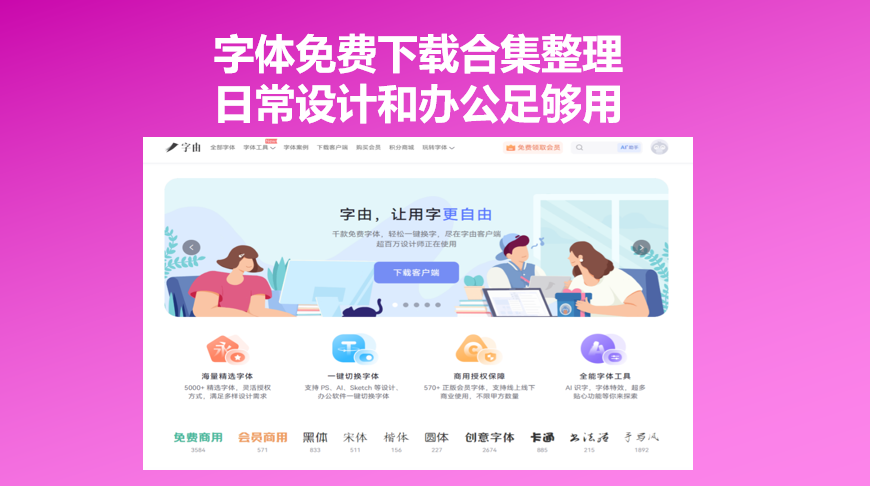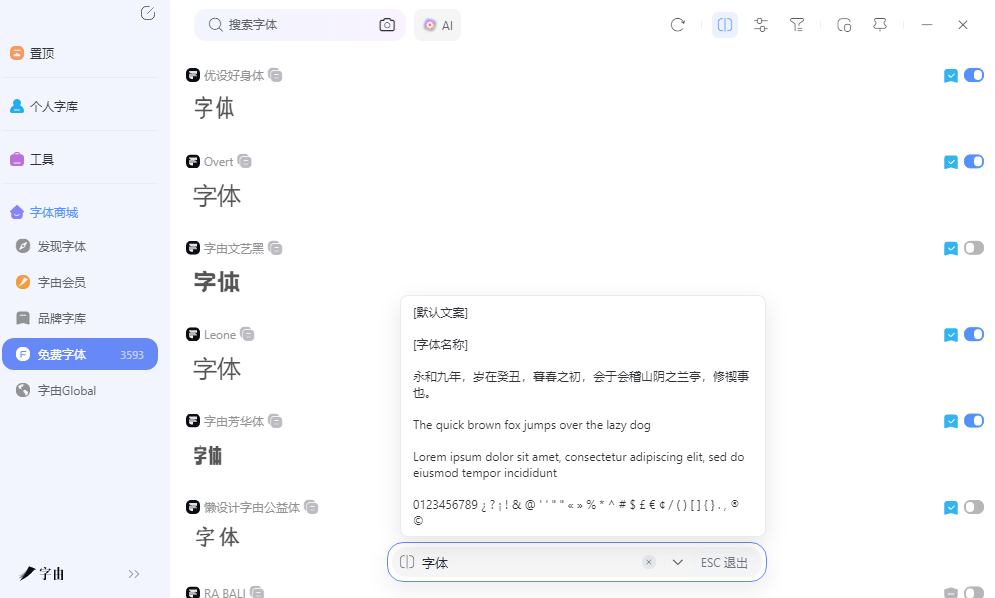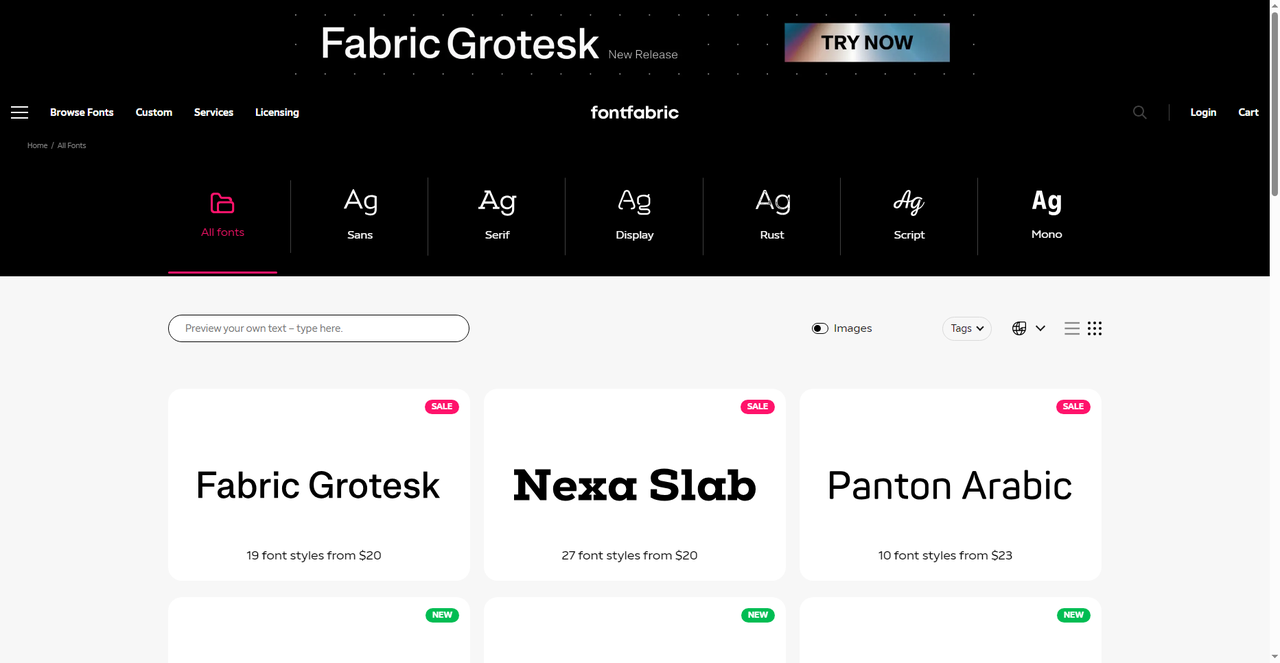
字体免费下载合集整理,日常设计和办公足够用
整理电脑里的字体文件夹,发现里面塞满了从各个论坛、网盘下载的文件,有些连名字都是乱码,有些安装后显示异常,还有些根本不知道能不能商用。其实与其零散地到处搜,不如直接收藏几个靠谱的字体免费下载平台,按需取用反而更高效。这篇文章整理了五个实用网站,从中文到英文、从通用到特殊场景都有覆盖,每个平台都标注了授权信息和适用场景,日常设计和办公基本够用了。
字由中明确标注可免费商用的中文字体超过三千款,但是很多人平时搜集字体,文件夹命名乱七八糟,真到做项目时却想不起来哪款能商用,但是字由把授权信息直接标在每款字体的详情页,免费商用标签一眼就能看见,勾选后列表里只剩能放心用的选项,做公司 PPT 或者商业海报时从这里挑,后续不用担心。
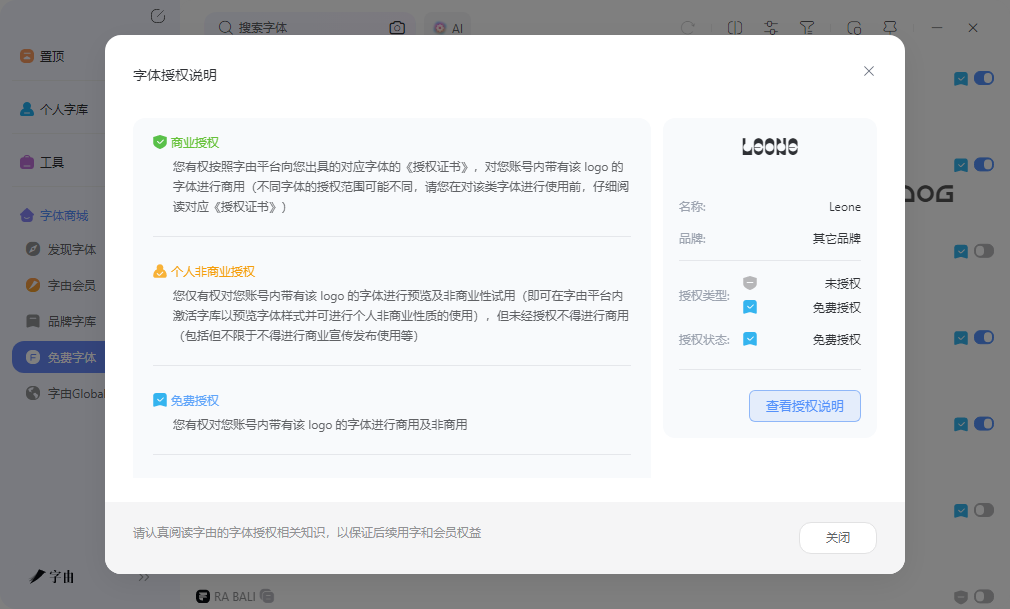
浏览方式也做了不少优化。除了常见的黑体、宋体、楷体、行书这些基础分类,还按使用场景和视觉气质做了细分。比如要做年会海报,直接点进喜庆或者中国风标签;要做科技类 PPT,筛选现代或者商务分类。这种按场景找字的方式比按书体名称翻找更直观,尤其是对字体知识不多的办公用户来说,看到标签就能大概猜出风格方向,找字体免费下载资源时效率提高不少。
预览环节也省了不少事。传统方式是先下载安装,再到软件里试效果,不合适再卸载,来回折腾。字由支持在预览框里直接输入自己的文案,字号、背景色都能调,看到实际排版效果再决定要不要激活。这个细节对判断字体在真实项目中的表现很管用,同样的字体显示不同内容,视觉感受可能差很多。遇到合适的点一下收藏,自动归到个人分组里,下次做同类项目直接打开分组调用,不用重新翻找。
而且字由对跨设备同步对多机工作的人比较友好。公司电脑上整理好的收藏和分组,回家登录同一个账号全部都在。换电脑或者系统重装后,登录账号就能恢复之前的字体设置,省去了重新下载安装几百款字体的麻烦。对于需要长期维护一套稳定字体免费下载资源的设计师和办公用户来说,这种云端备份比本地文件夹管理靠谱得多。
2、FontFabric
FontFabric 是一个专业字体厂商网站,首页展示了 Fabric Grotesk、Nexa Slab、Panton Arabic 等多款字体家族。每款字体都提供了详细的字重展示和风格预览,用户可以在搜索框里输入自己的文案测试效果。FontFabric 的字体质量比较高,很多字体家族包含多个字重和变体,适合做品牌 VI 或者完整排版系统。部分字体提供字体免费下载选项,下载前可以确认授权范围。对于需要高质量英文字体资源的设计师来说,这个平台的专业度比较可观。字体文件一般是 OTF 或 TTF 格式,安装到系统后就能在各类设计软件里调用。平台的界面设计简洁现代,浏览体验比较流畅,字体展示图清晰,能快速判断风格是否符合项目需求。
3、ReceiptFont
ReceiptFont 是一个专注收据和小票字体的特色平台,收录了超市收银机、热敏打印机常见的字体样式。首页展示了 Walmart、CVS、Target 等商场小票上常见的字体效果,包括点阵字体、等宽字体等类型。这些字体在日常生活中很常见,但普通字体库很少收录。对于需要模拟真实收据效果、做复古设计或者研究收银系统字体的用户来说,ReceiptFont 提供了很精准的字体免费下载参考。每款字体都标注了使用场景和来源说明,下载前可以了解清楚。字体文件格式通用,安装后在 Photoshop、Illustrator 里可以直接调用,做复古海报或者模拟小票的设计时很有特色。这个平台的资源虽然小众,但在特定场景下很难被替代,属于设计师工具箱里的特殊储备。
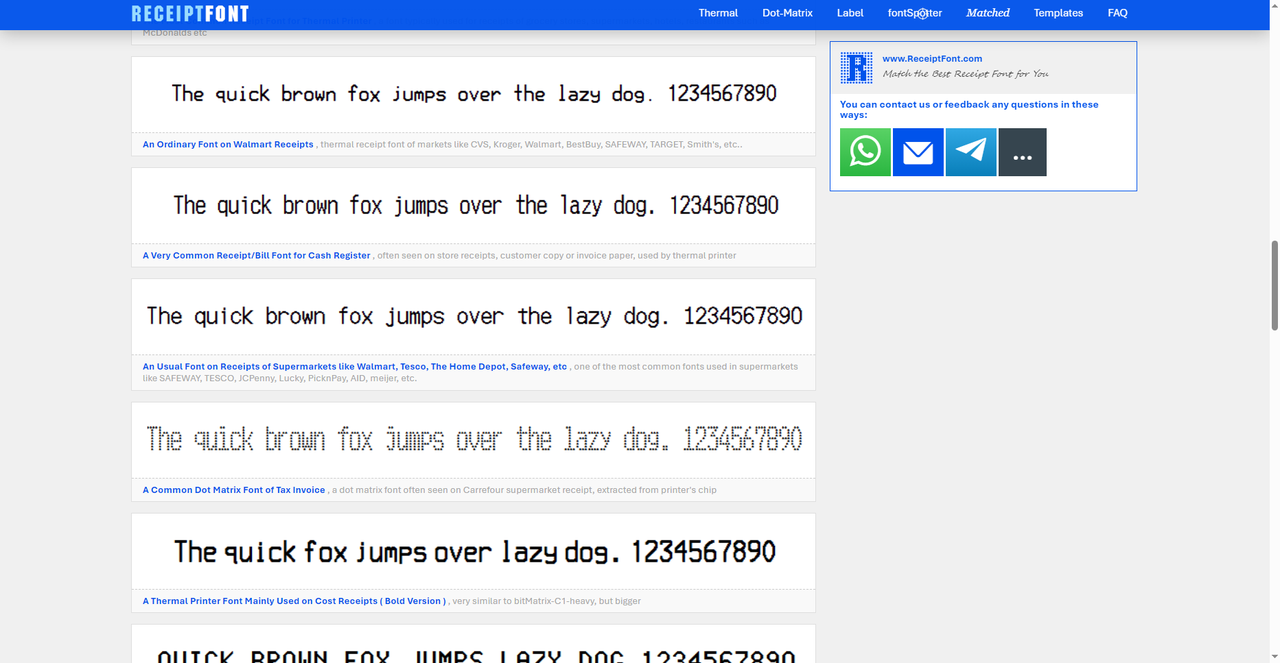
4、Cufon Fonts
Cufon Fonts 是一个字体集合平台,按主题整理了多个字体合集,包括 Happy Birthday Fonts、Editorial Fonts、Chinese Style Fonts、Tattoo Fonts、Study Fonts、Cinematic Fonts、Science Fonts 等。每个合集收录了风格相近的字体资源,方便用户按场景快速定位。比如做中国风海报可以直接浏览 Chinese Style Fonts 合集,做生日贺卡可以查看 Happy Birthday Fonts。平台的浏览方式比较直观,通过封面图就能判断合集的整体风格。部分字体支持字体免费下载,下载前需要确认具体授权信息。对于喜欢按主题探索字体、随机发现新资源的用户来说,这种合集整理方式比较省心。合集的更新频率比较稳定,经常会有新的主题加入,定期浏览可以发现一些意想不到的资源。
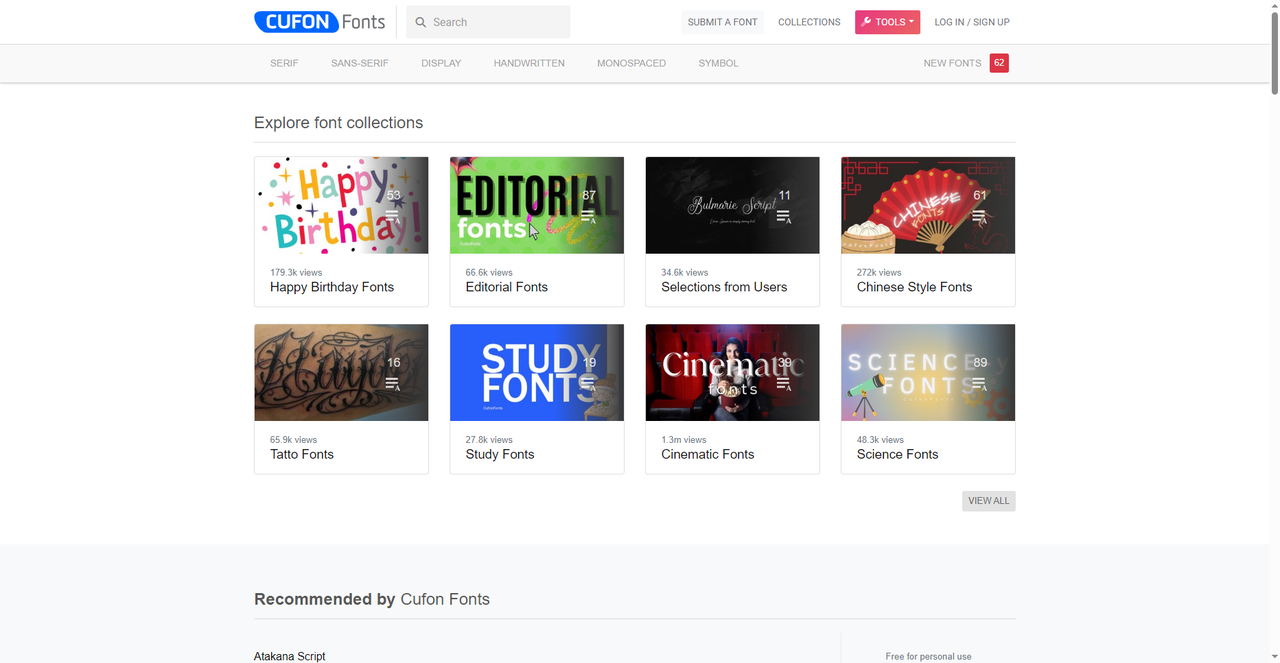
5、Font Squirrel
Font Squirrel 以 Free Font Utopia 为理念,专门收集经过人工筛选的高质量免费字体。首页展示的 Acherus Grotesque、Intro Rust、Source Sans Pro、Open Sans、Questa 等热门字体,每款都标注了字重数量和厂商信息,提供 OTF 或 TTF 格式下载。平台的筛选标准比较严格,收录的字体都经过商用授权审核,下载前可以查看详细的许可说明。对于需要确保版权合规、又不想花钱购买字体的设计师和办公用户来说,这个平台省去了逐个确认授权的麻烦,是字体免费下载的放心选择。字体文件下载后直接安装到系统,在 Word、PowerPoint 等办公软件里就能调用,日常文档排版和基础设计足够应付。平台还提供了 Webfont Generator 工具,可以把字体转换为网页字体格式,对前端开发人员比较实用。
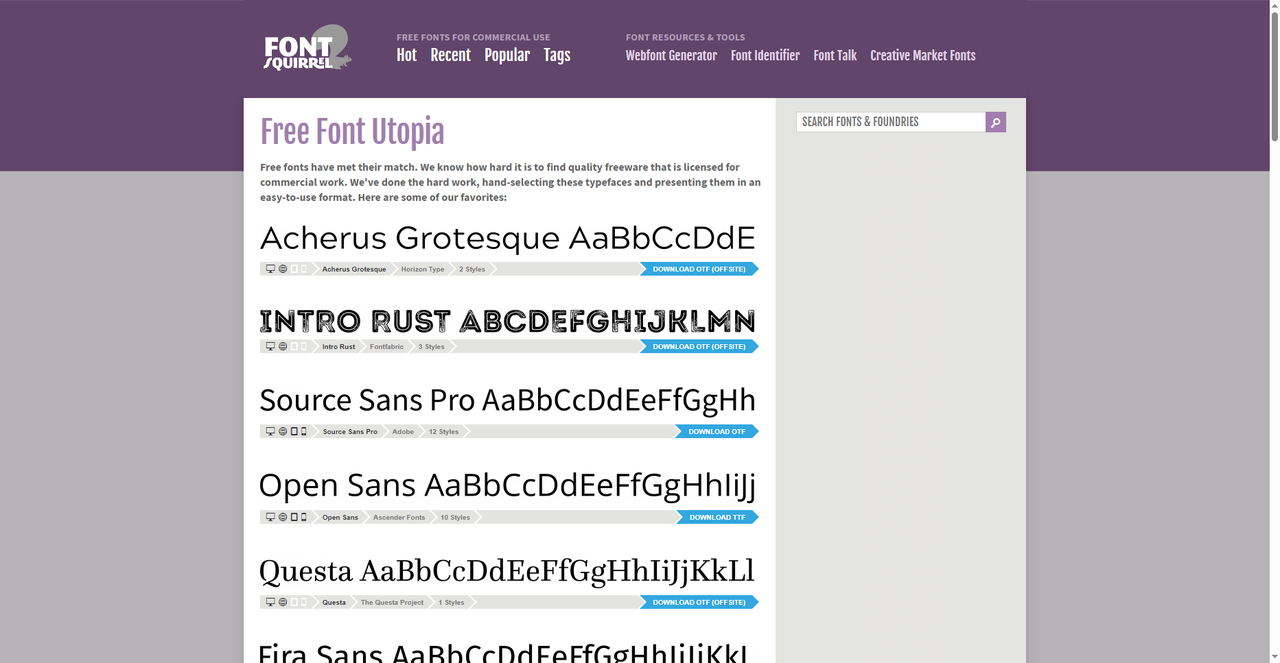
做公司 PPT 或者商业海报,字由的免费商用筛选和一键激活最省心,中文资源也全,是字体免费下载后立刻能用的选择。FontFabric 适合对英文字体质量要求高、需要多字重家族的项目。ReceiptFont 比较小众,做复古小票或者收银机风格设计时才用得上。Cufon Fonts 按主题逛比较有意思,适合没明确目标、想随机找灵感的时候。Font Squirrel 授权最放心,英文办公字体直接从这里下载基本不会踩雷。